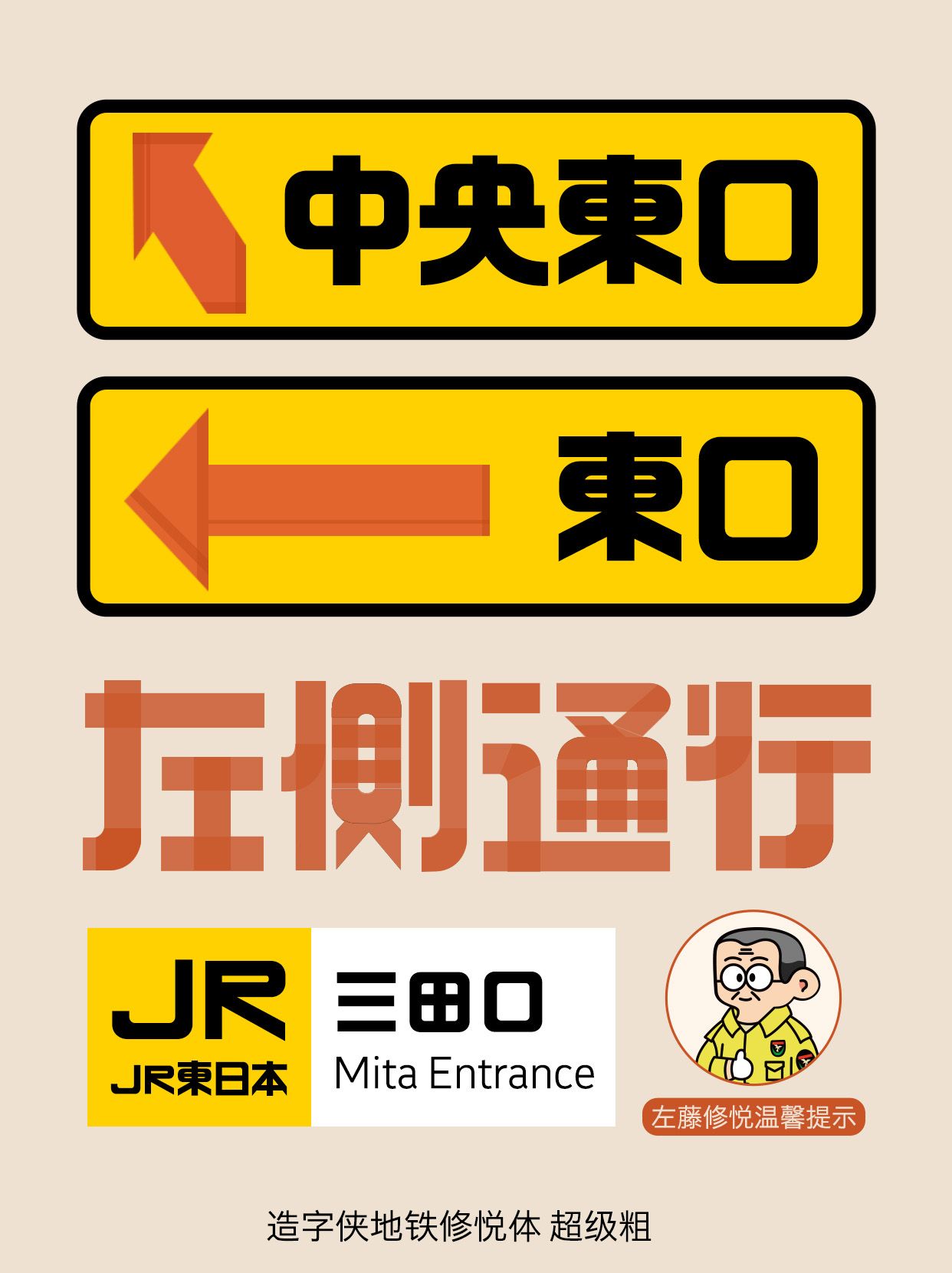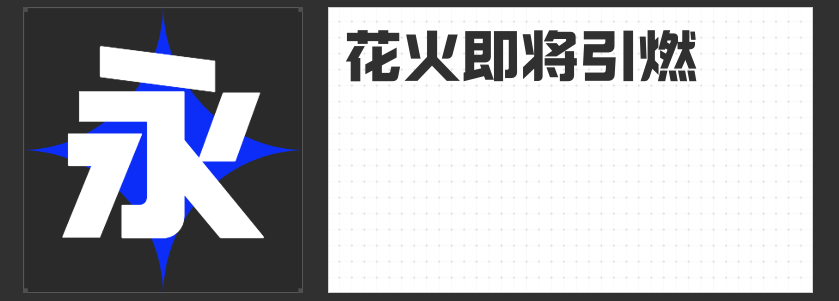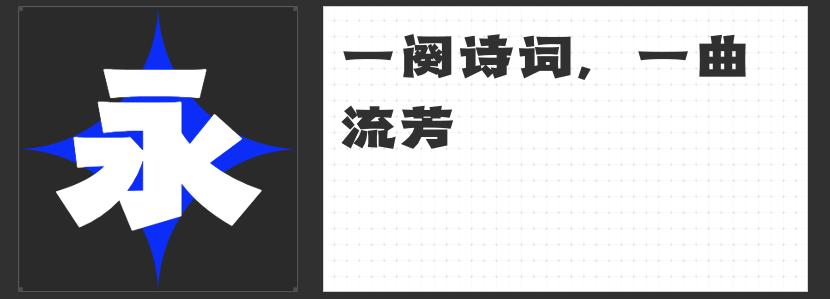
包装设计新宠:四款创意字体推荐
在包装设计中,字体不仅是传递信息的媒介,更是展现品牌个性和产品特色的重要元素。今天,就为大家推荐四款适用于包装的创意字体,它们各具特色,定能为你的设计增添亮点。
这款字体以其粗犷有力的线条和简洁明快的风格著称,非常适合用于强调产品名称或关键信息。在包装设计中,励字勇敢黑简 特黑能够瞬间抓住消费者的眼球,传递出产品的力量感和可靠性。无论是男性用品、运动装备还是工业产品,这款字体都能完美匹配,彰显品牌的大气与稳重。
2.造字侠朝凤宋简
造字侠朝凤宋简以其优雅细腻的笔画和古朴典雅的气质,成为传统文化与现代设计融合的典范。在包装设计中,这款字体适用于传递古典韵味和文化底蕴的产品,如茶叶、文具、手工艺品等。它能够营造出一种温馨、怀旧的氛围,让消费者在品味产品的同时,感受到深厚的文化底蕴。
这款字体以其独特的造型和鲜明的个性,成为包装设计中的一股清流。超级粗的笔画让文字在视觉上更加突出,非常适合用于吸引年轻消费者的注意力。在潮流服饰、时尚配饰、创意礼品等包装设计中,造字侠地铁修悦体 超级粗能够展现出产品的时尚感和个性魅力。
4.造字侠热辣隶简
造字侠热辣隶简以其独特的隶书风格和火辣的视觉冲击力,成为包装设计中的一大亮点。这款字体适用于传递热情、活力、动感的产品信息,如饮料、零食、运动产品等。它能够营造出一种热烈、欢快的氛围,激发消费者的购买欲望。
以上四款字体各具特色,适用于不同类型的包装设计。选择适合品牌和产品特性的字体,将大大提升包装的吸引力和市场竞争力。